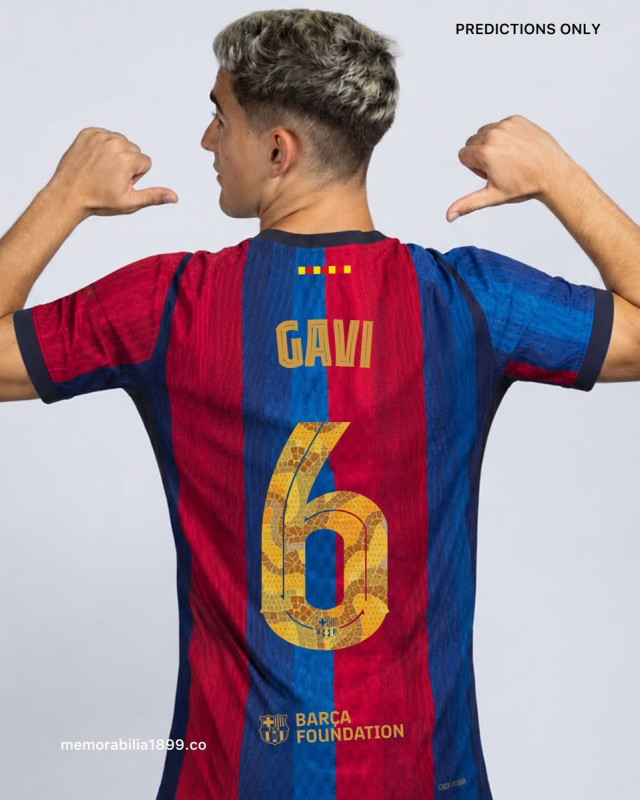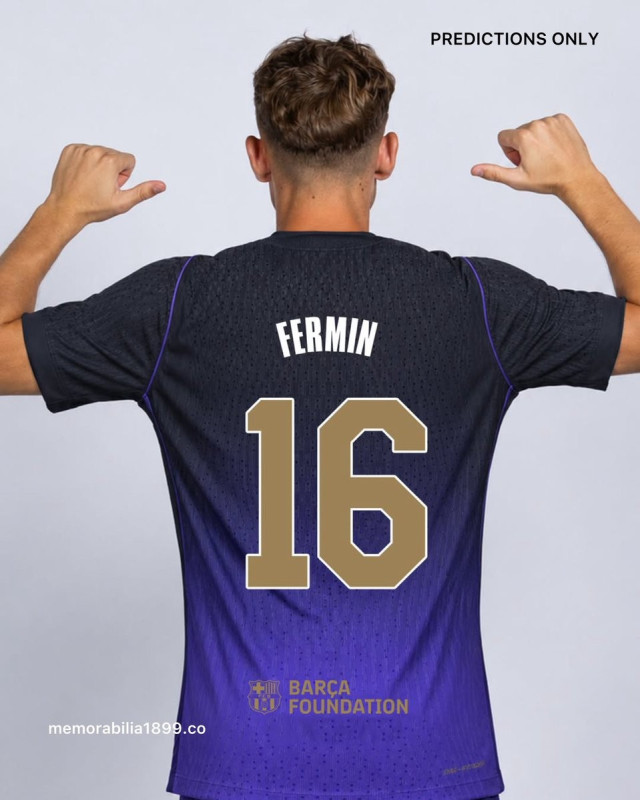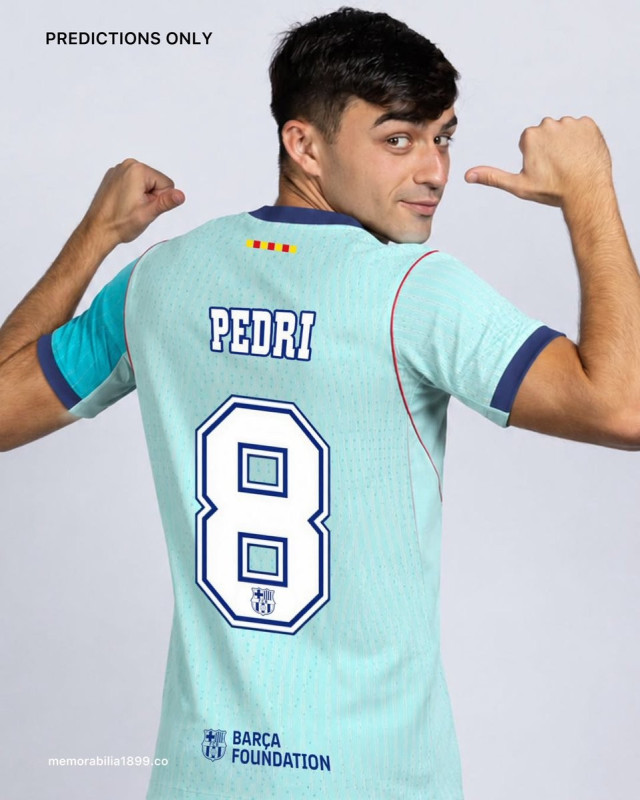
GELEAKT: Der FC Barcelona bekommt in der Saison 26/27 für jedes Trikot eine eigene Schriftart
- Eigene Schriftarten pro Trikot: Der FC Barcelona wird in der Saison 2026/27 für jedes seiner drei Pokal-Trikots eine einzigartige und maßgeschneiderte Schriftart einführen, was eine Premiere für den Verein darstellt.
- Hintergrund der maßgeschneiderten Designs: Aufgrund der La-Liga-Vorschrift, seit 2017 eine einheitliche Standardschriftart für Ligaspiel-Trikots zu verwenden, nutzt Barcelona für Pokalwettbewerbe wie die UEFA Champions League und Copa del Rey traditionell individuelle Schriftarten.
- Inspiration der spezifischen Schriftarten: Die Schriftart des Heimtrikots ist von Gaudí inspiriert, die des Auswärtstrikots ist im Stil der Los Angeles Lakers gehalten und die des dritten Trikots lehnt sich an das Kappa-Trikot von 1992 an.
Nach seinem Teaser hat der FC-Barcelona-Trikot-Experte @memorabilia1899 ein paar echt interessante Neuigkeiten für Barca-Fans parat. Barcelona wird für die Saison 2026/27 nicht nur eine neue Schriftart für die Trikots einführen, sondern eine maßgeschneiderte für jedes einzelne Trikot.
Seit 2017 schreibt die La Liga für alle Vereine in Ligaspielen eine einheitliche Standardschriftart vor. Deshalb hat Barcelona traditionell eigene, maßgeschneiderte Schriftarten vorgestellt, wie zum Beispiel die in der Saison 2019/20 vorgestellte „Barcelona Play“-Schrift, die in der UEFA Champions League und der Copa del Rey zum Einsatz kam. Zum ersten Mal überhaupt werden die Fans in den Pokalwettbewerben von Barcelona drei einzigartige und stark stilisierte, maßgeschneiderte Schriftarten zu sehen bekommen.
FC Barcelona 26/27 – Schriftarten für die Pokal-Trikots
Auch wenn es sich ausdrücklich um Prognosen und nicht um offizielle Leaks handelt, bieten die Entwürfe einen interessanten Einblick in die Schriftgestaltung der Heim-, Auswärts- und Ausweichtrikots von Barcelona für die Saison 2026/27.
Schriftart des Barcelona-Heimtrikots 2026/27
Für das Trikot der Saison 2026/27 setzt Barcelona auf ein von Gaudí inspiriertes Design und zollt damit dem berühmten katalanischen Architekten Tribut.
Schriftart des Barcelona-Auswärtstrikots 2026–27
Die Schriftart für das Barça-Auswärtstrikot ist im Stil der Los Angeles Lakers gehalten und passt perfekt zum Mamba-Branding.
Schriftart des dritten Trikots von Barcelona 2026/27
Abgerundet wird das Set durch die vom Kappa-Trikot von 1992 inspirierte Schriftart des dritten Trikots.